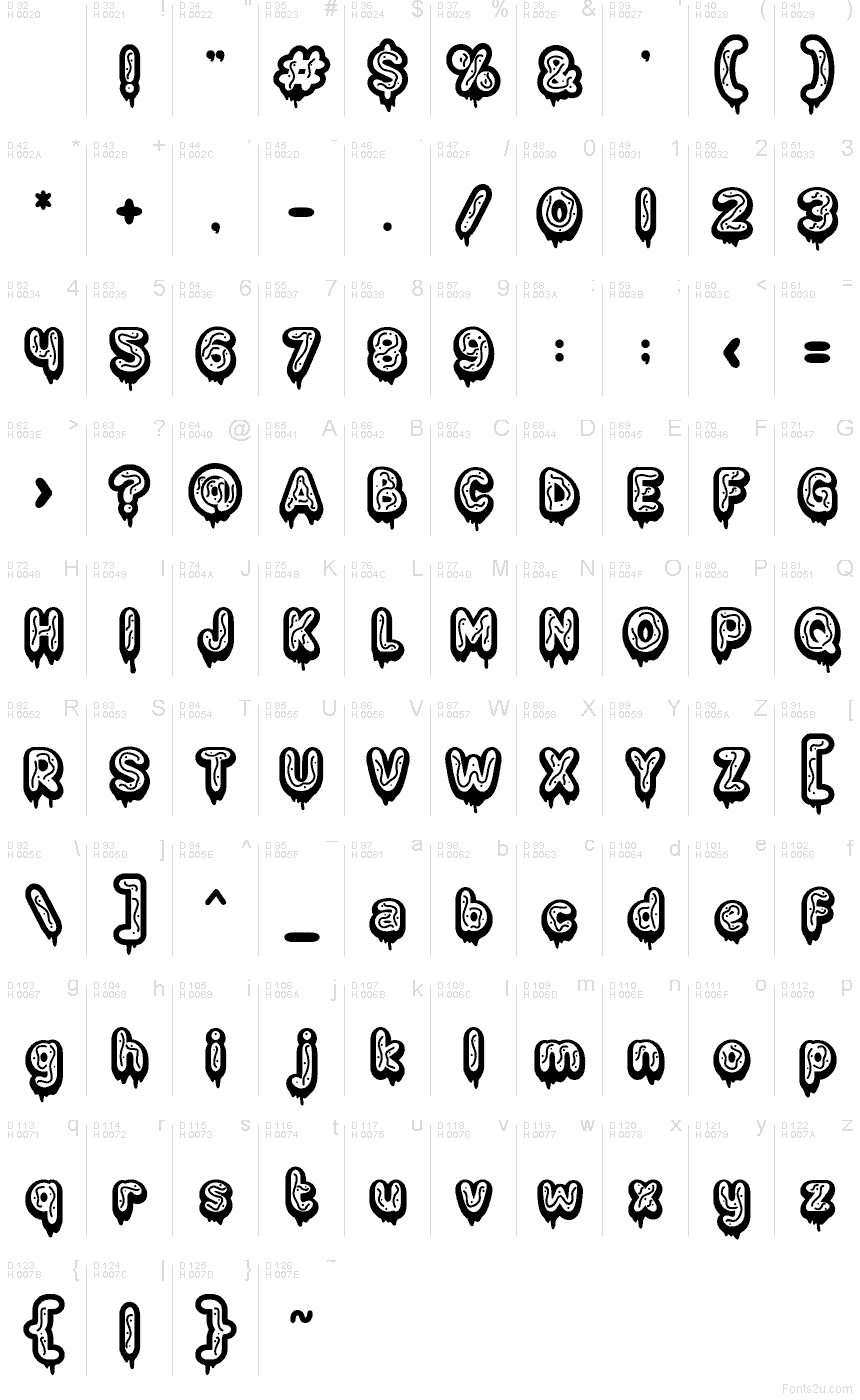
Cake Couture Seven
Cake Couture Seven von Putracetol Studio ist eine kostenlose Display-Schriftart im Frosting-Stil, die durch ihre cremige, von Hand aufgetragene Optik besticht. Die Buchstaben wirken wie dicke Zuckerguss-Verzierungen, die leicht zu verlaufen scheinen. Mit ihren abgerundeten Formen, den tropfenden Unterseiten und verspielten Details im Inneren wirkt sie eher wie liebevoll dekorierte Backkunst als wie eine starre geometrische Konstruktion.
Sie eignet sich perfekt für Branding im Bäckereibereich, Einladungen zu Geburtstagen, Süßwarenverpackungen, Poster-Überschriften und Titelkarten in sozialen Medien – überall dort, wo eine kostenlose Schrift mit einer süßen, leicht geschmolzenen Note gefragt ist. Setzen Sie sie ein, wenn Sie kurzen Namen, Headlines oder Logos einen hausgemachten Look verleihen möchten, da die weichen Formen und die kleinen Tropf-Details für sich sprechen.